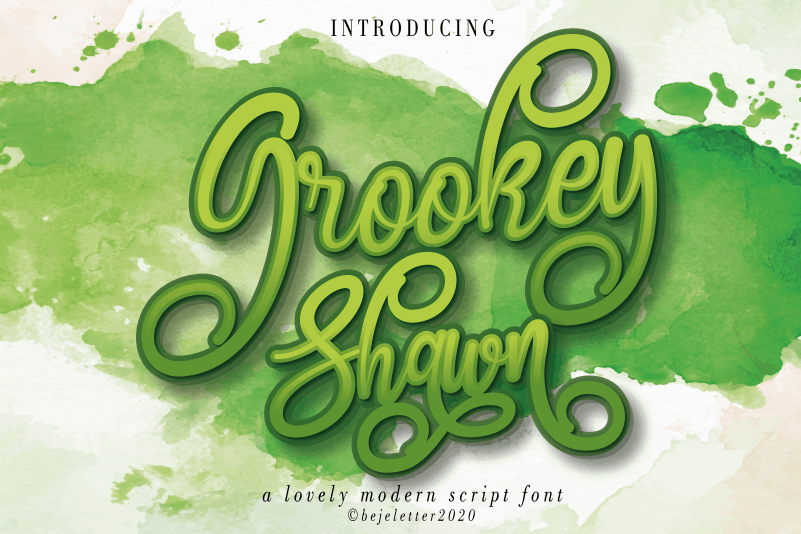
Grookey Shawn Script Font – Download Grátis
A Grookey Shawn Script Font é uma elegante tipografia feita à mão com traços que dançam ao longo do nível de base. Esta fonte romântica e deliciosa tem um toque casual, mas também sofisticado. Ela se destaca não apenas para uso em logotipos ou mensagens importantes, como também para cartões de casamento, cabeçalhos, camisetas, assinaturas, marcas de sinalização, rótulos, folhas de notícias e até mesmo quadros, badges. Seu estilo atraente faz do Grookey Shawn Script Font uma escolha perfeita para qualquer projeto que deseje dar um toque especial e pessoal. Englobe-a em seus projetos e permita-se ser surpreendido com os resultados únicos e criativos da sua nova fonte de texto!
Designer: bejeletter